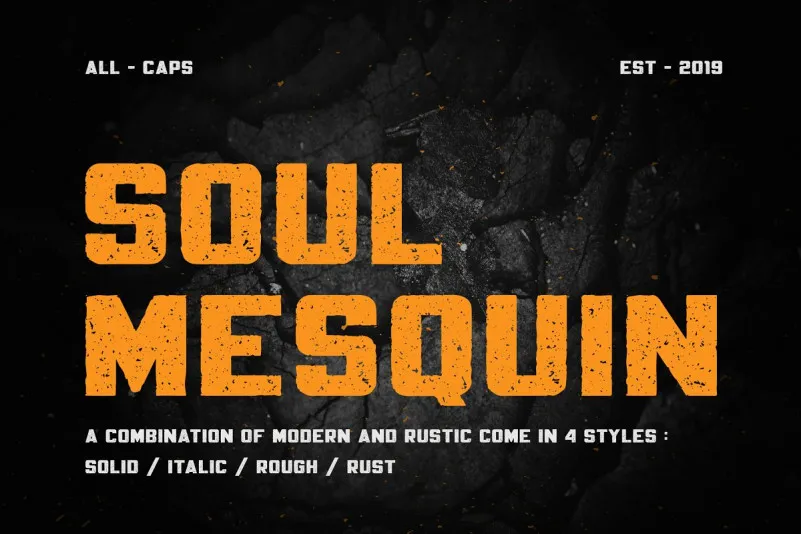
Olá amantes do tipo! Introduzimos Mesquin Typeface, uma combinação de modernidade e rusticidade em quatro estilos únicos. Este é um texto tipográfico excepcional para conceitos modernos e fortes. Você vai adorar! Mesquin é uma fonte sans serif toda maiúscula com figuras geométricas dos caracteres. Inspirada nas letras da era industrial e velha, mas ainda mantém uma aparência moderna forte. Mesquin oferece opções de design versáteis e se destaca perfeitamente para headlines, logomarcas, posters, embalagens, camisetas personalizadas, cartões-postais e muito mais.